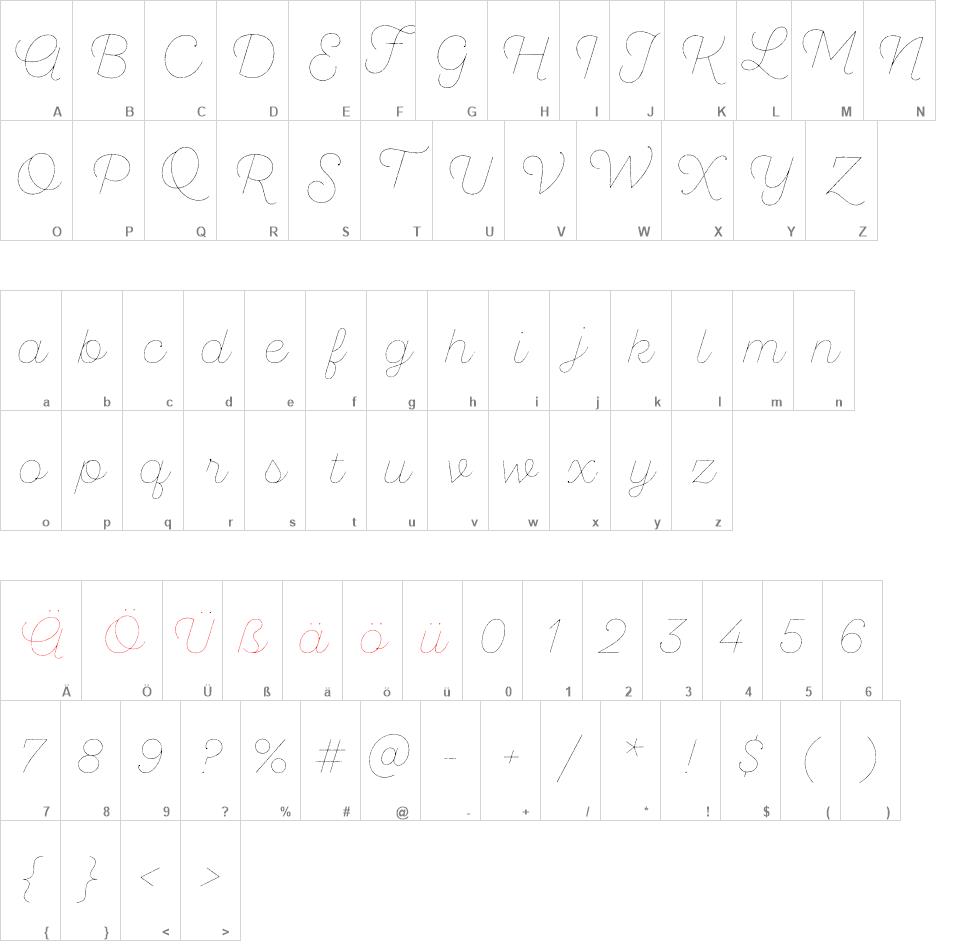
Sant’Elia Script
Sant’Elia Script  font
Das Sant'Elia Script aus dem Yellow Design Studio ist eine solide moderne Familie mit sechs Gewichten, regulären und rauen Versionen. Ihre Formen sind knackig und einladend und beleben. Alternative Versionen haben zusätzliche Energieeinspritzung der Schrägstriche. Grobe Gewichte enthalten drei verschiedene Gefahrenstufen, die zur zusätzlichen Kontrolle und Personalisierung gemischt werden können. Testen Sie Sant'Elia Rough Line, Line Two und Line Three kostenlos!